男孩“印刷字体”火了,获700万点赞,父母却难展笑容:他生病了
我们常说,看一个人先看他是字,一个人的性格都会体现在他的字上面,可有这么一个男孩,他的字就像印刷上去的一样,可他的故事却让人心酸。
男孩“印刷字体”火了,获700万点赞,父母却难展笑容:他生病了
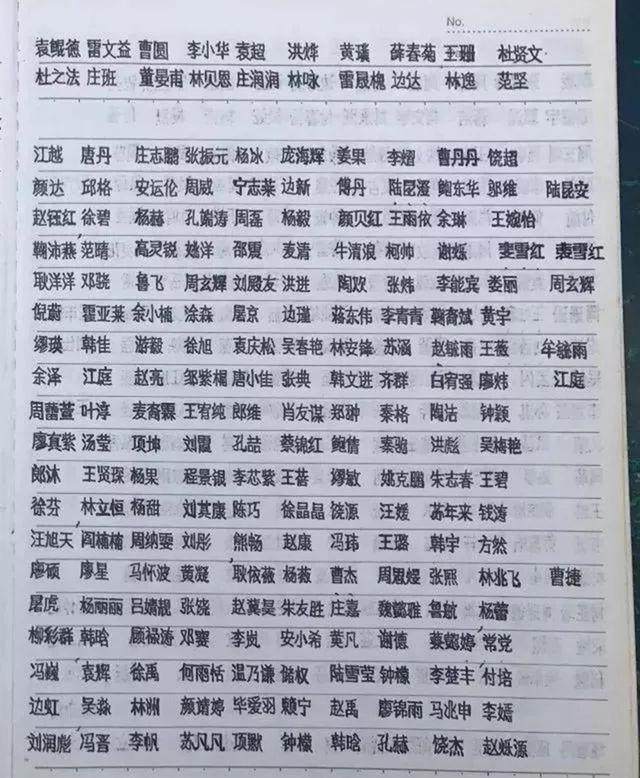
上面这些字,看着像打印机印刷在纸上的,可却是实打实手写出来的手写体,很多网友并不相信,谁的字能这么工整,字这么小还不乱,字间距都跟计算好了一样。
其实写这些字的人,是来自浙江的一个16岁男孩林文彬,因为写着一手“印刷字体”,林文彬一下子就火了起来,网友点赞已经超过700万了。